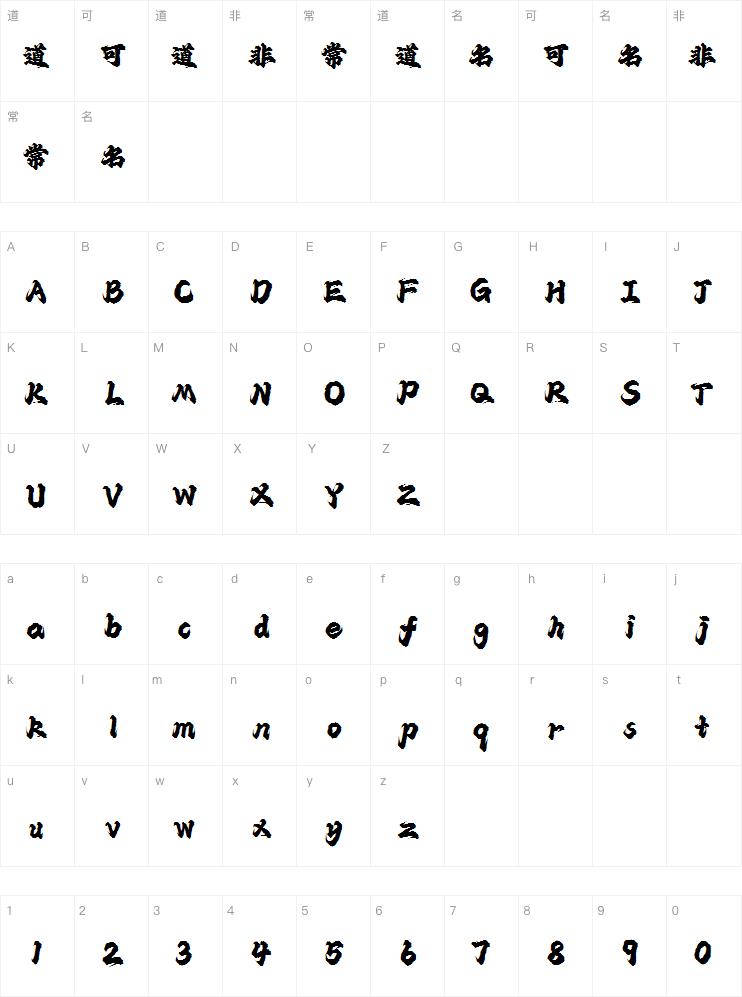
潮字社形意拳简繁 苍劲以拳意下笔,是一款有着形意拳朴实简练、内外合一的独特风格的毛笔字体。字体整体结字规整、布局匀称,内意与外形高度统一。笔画方圆兼备、墨色浓厚,起收笔出锋利落有型;运笔动作朴实沉稳,笔画粗细自然过度且带有牵丝连带,书写连贯性得以提升,总体具有沉稳、和谐的视觉感受。适用于标题字、海报、文创、书籍封面、影视娱乐等多种应用场景。